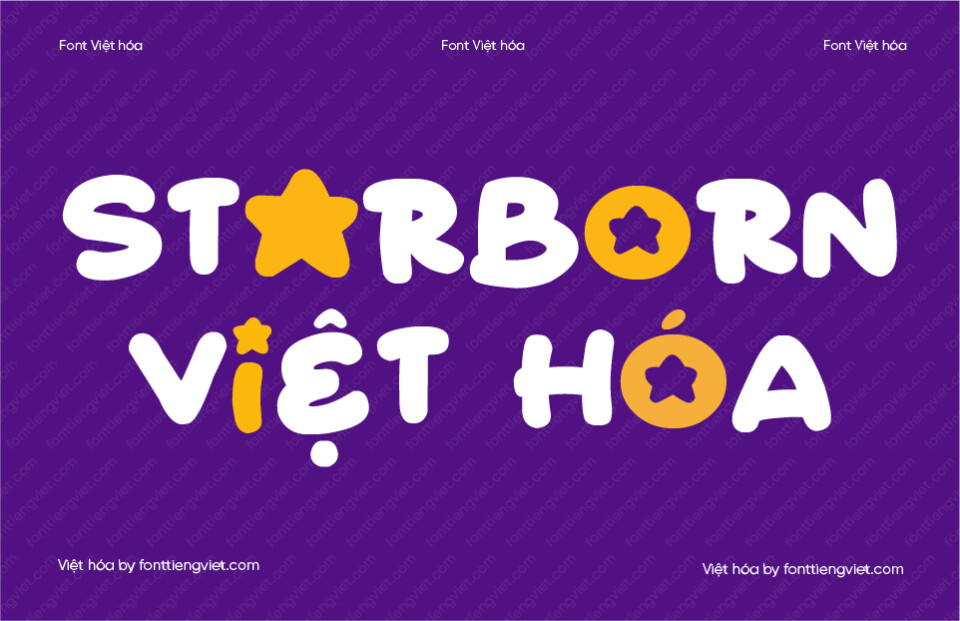
Font Việt hóa 1FTV VIP Starborn
Font Việt hóa 1FTV VIP Starborn – Bộ Font Chữ Gaming Đỉnh Cao Cho Thiết Kế
Giới thiệu về Font Việt hóa 1FTV VIP Starborn
Trong thế giới đồ họa hiện đại, việc lựa chọn một Font Miễn Phí chất lượng luôn là ưu tiên hàng đầu của các nhà sáng tạo. Font Việt hóa 1FTV VIP Starborn nổi lên như một hiện tượng trong cộng đồng thiết kế nhờ phong cách mạnh mẽ và cá tính. Đây là phiên bản được tinh chỉnh kỹ lưỡng, hỗ trợ đầy đủ bộ gõ tiếng Việt, giúp người dùng dễ dàng ứng dụng vào các dự án truyền thông mà không lo lỗi hiển thị. Với các đường nét bo tròn đặc trưng kết hợp cùng độ dày ấn tượng, bộ font này mang đến cảm giác hiện đại, năng động và vô cùng chuyên nghiệp.
Đặc điểm nổi bật của Font Việt hóa 1FTV VIP Starborn
Phong cách thiết kế gaming độc đáo
Font Việt hóa 1FTV VIP Starborn sở hữu cấu trúc chữ dạng hình khối, tạo nên sự vững chãi và bắt mắt. Kiểu dáng này cực kỳ phù hợp cho các tiêu đề video trò chơi, biểu trưng của các đội tuyển Esports hoặc các banner quảng cáo sự kiện giải trí. Sự sáng tạo trong từng ký tự giúp tác phẩm của bạn trở nên nổi bật và thu hút thị giác ngay từ cái nhìn đầu tiên.
Khả năng ứng dụng đa dạng
Không chỉ giới hạn trong mảng gaming, bộ font này còn rất hữu ích cho học sinh và giáo viên khi thiết kế bài giảng điện tử hay báo tường. Nhờ tính dễ đọc và tính thẩm mỹ cao, nó giúp nội dung trình bày trở nên sinh động hơn. Bạn có thể sử dụng font cho các mục đích từ in ấn áo thun, làm poster cho đến thiết kế giao diện ứng dụng di động một cách linh hoạt.
Kết luận về bộ font chữ ấn tượng
Việc sở hữu Font Việt hóa 1FTV VIP Starborn sẽ giúp bộ sưu tập tài nguyên của bạn thêm phần phong phú. Đây là công cụ đắc lực để biến những ý tưởng sơ khai thành các tác phẩm nghệ thuật hoàn chỉnh. Đừng bỏ lỡ cơ hội nâng tầm thiết kế với Font Miễn Phí, Font Việt Hóa, Font Việt hóa 1FTV VIP Starborn để tạo nên những dấu ấn riêng biệt và đầy lôi cuốn trên mọi nền tảng số hiện nay.